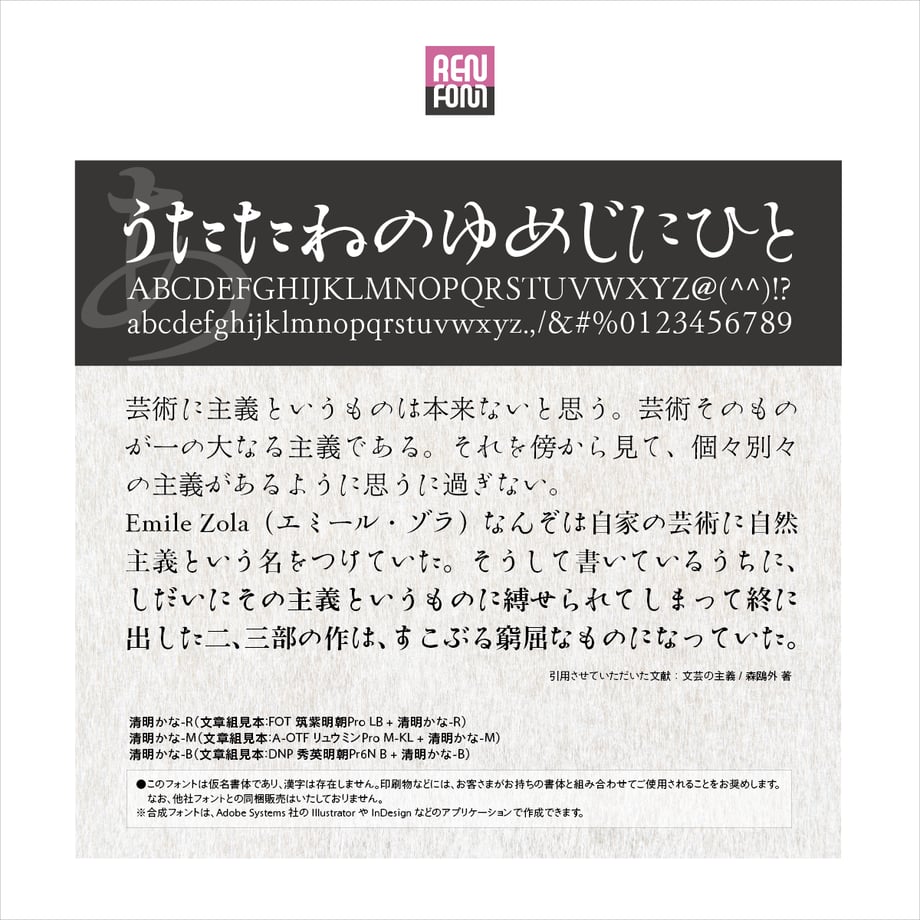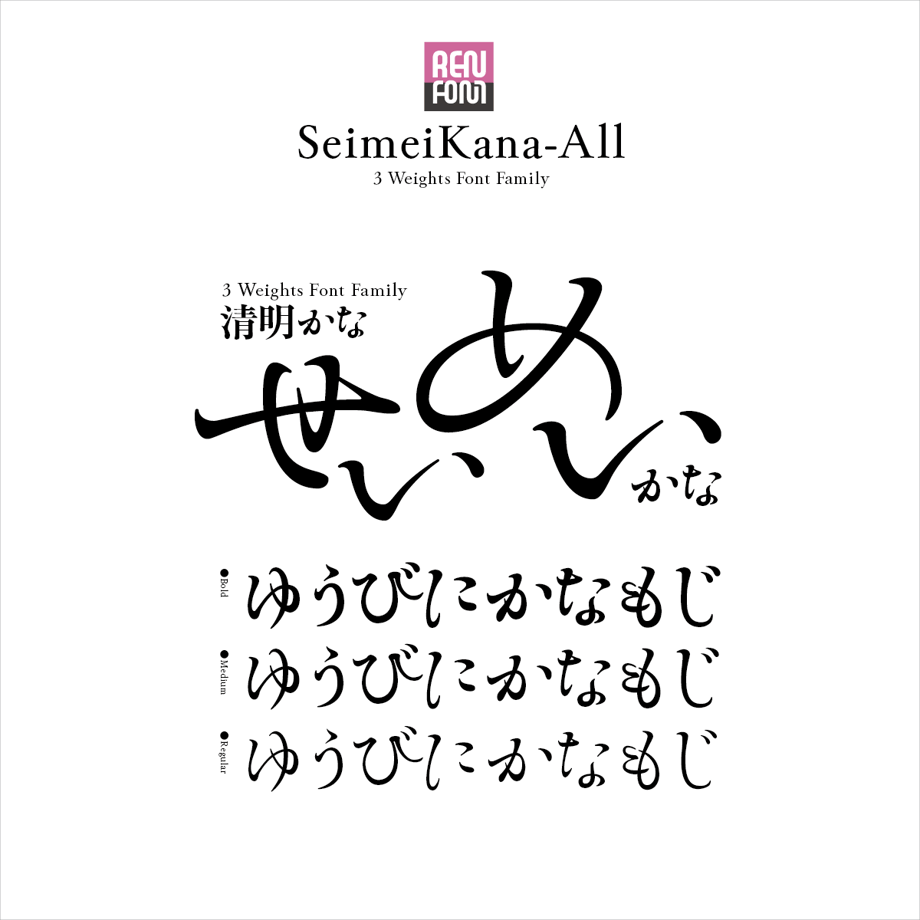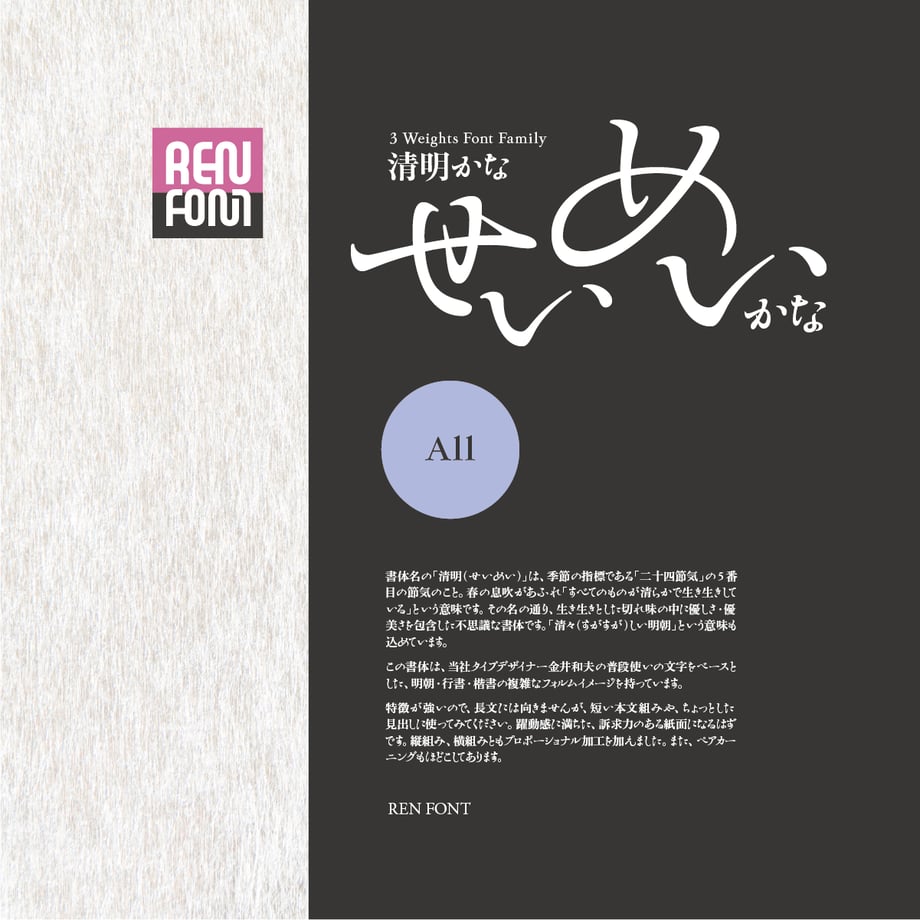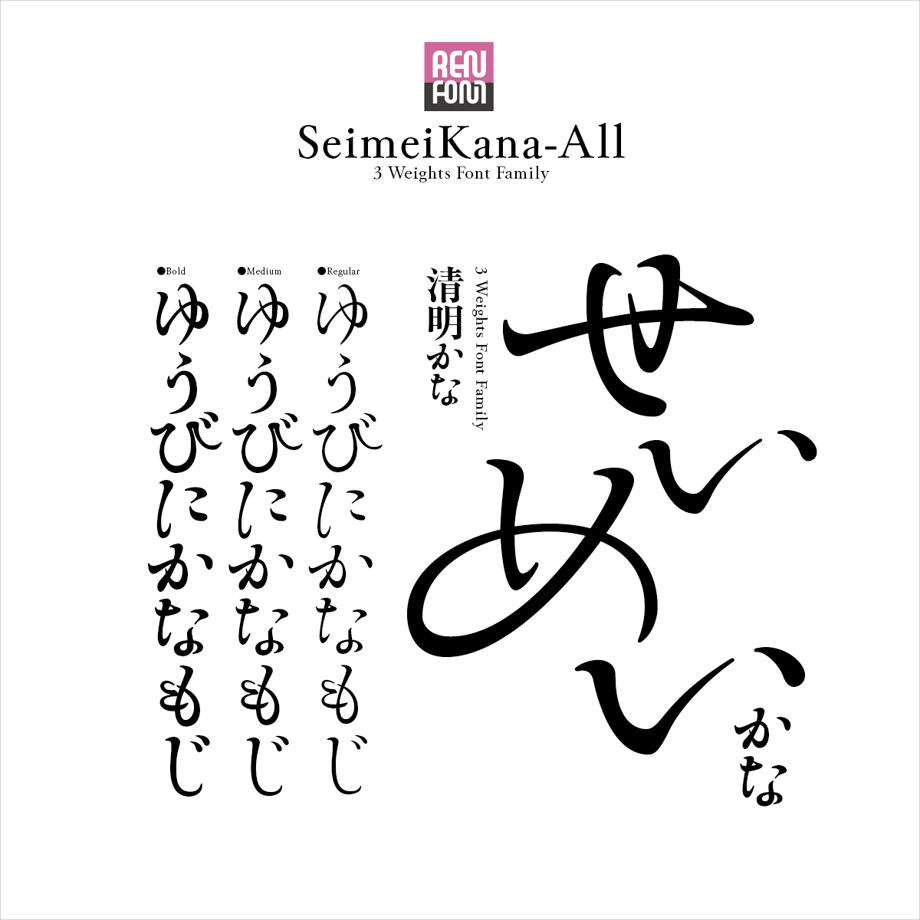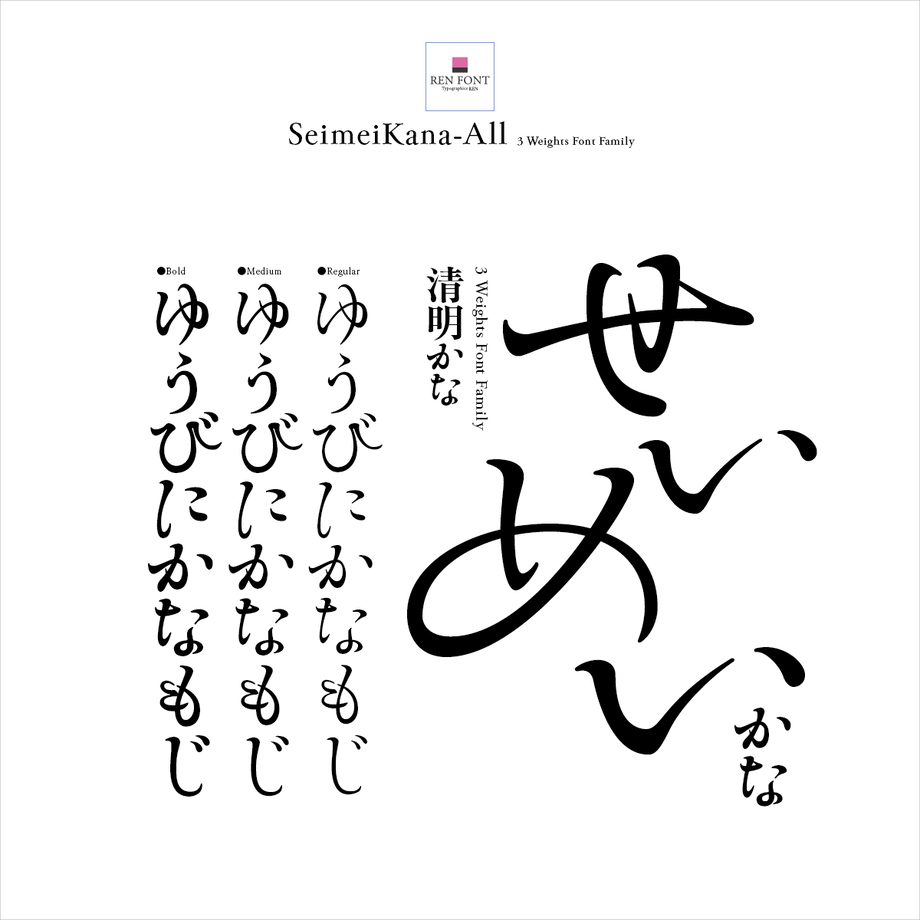
優しさと切れ味をあわせ持つ
清明かな 3ウェイトファミリー / OpenType
優しさと切れ味をあわせ持つ
書体名の「清明(せいめい)」は、季節の指標である「二十四節気」の5番目の節気のこと。春の息吹があふれ「すべてのものが清らかで生き生きしている」という意味です。その名の通り、伸びやかな切れ味の中に優しさ・優美さを包含した不思議な書体です。「清々(すがすが)しい明朝」という意味も込めています。
この書体は、当社タイプデザイナー金井和夫の普段使いの文字をベースとした、明朝・行書・楷書の複雑なフォルムイメージを持っています。「R(レギュラー)」、「M(ミディアム)」、「B(ボールド)」の、合計3ウェイトで構成されています。
また、オールドなイメージを残しつつも、その概念にとらわれず大仮名に設計してあるので、近代的な組版にも対応するマルチな性格を備えています。
躍動感と訴求力を表現する
清明かなファミリーの各書体は、クリエイティブワークに「躍動感と訴求力を表現する」一助にと開発しました。和文フォントは、正方形の中に押し込めることにより、伸びやかさがなくなる傾向があります。この書体は必ずしも正方形にとらわれない自由な発想で作られています。
特徴が強いので、長文には向きませんが、短い本文組みや、ちょっとした見出しに使ってみてください。躍動感に満ちた、訴求力のある紙面になるはずです。縦組み、横組みともプロポーショナル加工を加えました。また、ペアカーニングもほどこしてあります。
日本語文章の約70%はひらがな、カタカナが占めているといわれます。それだけに紙面の雰囲気を左右し、決定づける重要なアイテムです。
清明かなのウェイトは3つ。本文用のライトも、見出し・タイトル用のヘビー・ウルトラも用意していません。長文には向かないし、あまり太いとフォルムに矛盾が生じるからです。
そのフォルムは、しなやかでなめらか。払いを強調して舞踊のような躍動感を表現しました。先端は全て丸く処理、終筆も文字により独特の形にしてあります。正統からギリギリ踏み外さないよう細心の注意を払った、優美な書体です。
欧文・数字は、どちらかというと奔放な両かなとは異なり、クセの少ない伝統的なイメージにデザインしました。わずかに「K」「Q」「R」のテールに「かな」の雰囲気を持たせてあります。
格調高いGaramond調の形状ですが、若干現代風な設計になっています。欧文書体としての単独使用にも十分に耐えうる、和文付嘱書体としては稀な、非常に高い完成度を持っています。